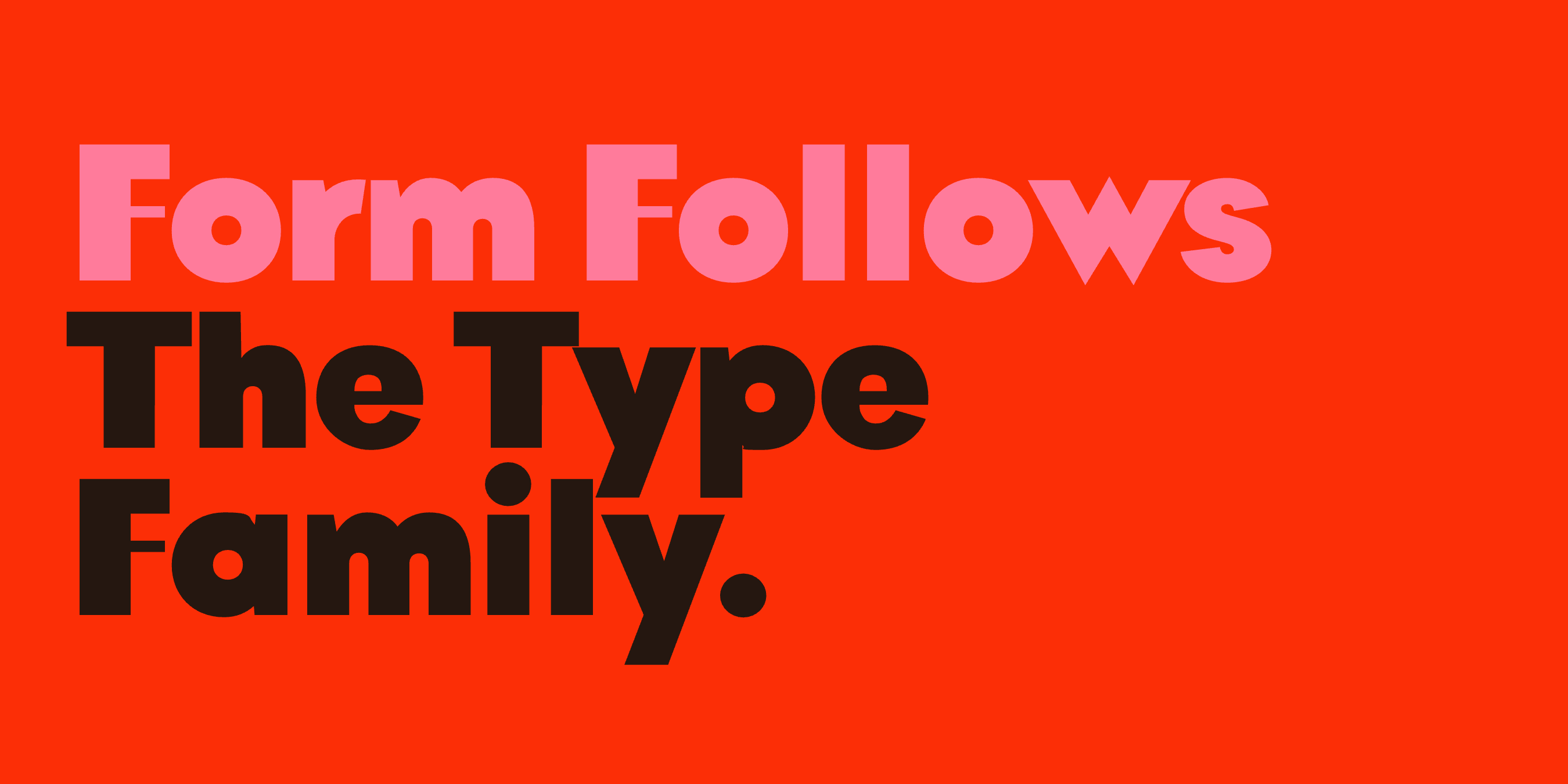
Bauhaus-Schriften: was eine Schrift zur Bauhaus-Schrift macht, und 11 zum Ausprobieren
Eine Bauhaus-Schrift besteht aus einfachen Formen: Kreisen, Bögen und geraden Linien, mit einer einheitlichen Strichstärke und ohne Verzierung. Dieser Ratgeber zeigt, woher dieser Stil kommt, woran man ihn erkennt, und 11 Schriften in diesem Stil, jede mit neun Schnitten und einer variablen Schrift.
Was eine Schrift zur Bauhaus-Schrift macht
Das Bauhaus war eine Gestaltungsschule, 1919 von dem Architekten Walter Gropius gegründet. Als sie 1925 in ihr eigenes Gebäude in Dessau zog, lief das Wort BAUHAUS in hohen, schlichten Großbuchstaben senkrecht an der Fassade hinunter. Im selben Jahr zeichnete Herbert Bayer, der an der Schule unterrichtete, sein Universalalphabet: nur Kleinbuchstaben, aufgebaut aus Kreisen, Bögen und geraden Linien. Eine eigene Schrift hat die Schule nie veröffentlicht. Bayers Alphabet blieb eine Zeichnung, bis Ed Benguiat und Victor Caruso daraus 1975 die ITC Bauhaus machten, die Schrift, an die die meisten beim Namen denken.
Die Futura, 1927 von Paul Renner gezeichnet, beruht auf denselben Ideen, obwohl Renner nie an der Schule unterrichtet hat. Erkennen lässt sich der Stil an diesen Merkmalen:
- Ein rundes o, nahezu ein perfekter Kreis.
- Ein einstöckiges a, oft auch ein einstöckiges g.
- Striche in einer Stärke, mit wenig oder keinem Kontrast.
- Buchstaben aus denselben wenigen Bauteilen, die sich deshalb ähneln.
11 Bauhaus-Schriften
Bauhaus Geo
Die Schrift in dieser Liste, die Bayers Alphabet am nächsten kommt. Das o ist ein Kreis, das a einstöckig, und der Strich hat eine einheitliche Stärke. Alternative Buchstaben machen sie geometrischer oder im Text besser lesbar. Für Architektur, Tech und minimalistische Marken.
Scal kommt in dieser Liste der Futura am nächsten: ein rundes a und o, spitze Enden an A, M, N, V und W und scharfe Schnitte an C, G und S. Die leichten Schnitte eignen sich für längere Texte, die kräftigen sind kompakt. Für Mode- und Beauty-Labels, Magazine und Restaurants.
Vole besteht aus Kreisen und geraden Linien wie die Bauhaus-Alphabete, mit kräftigeren, weicheren Formen. Die Punzen sind rund, a und g sind einstöckig, und die Strichenden sind gerade. Fünf Stilsets bieten andere Formen für a, g, M, N und mehr. Für Logos, Plakate und Verpackungen.
Eine runde Sans mit einfachen, modularen Formen: M und N sind oben gerundet wie das o. Sie wirkt freundlich und bleibt auch in kleinen Größen gut lesbar. Oft für Lifestyle-Marken und Konsumgüter verwendet und eine gute Sans für die Kombination mit Bauhaus Soft.
Die einzige Serifenschrift in dieser Liste. Eine kräftige, organische Serifenschrift mit weichen Ecken und etwas Kontrast zwischen dicken und dünnen Strichen. Sie ist unsere meistverkaufte Schrift. Für Beauty, Lifestyle, Verpackungen und Editorial, und sie passt zu jeder der Sans-Schriften hier.
Eine runde Schrift mit starkem Kontrast zwischen dicken und dünnen Strichen. Für Beauty-Marken, Verpackungen und Modemagazine.
Eine schmale Sans für Startup- und Tech-Branding, weniger geometrisch als Geo. Für Produktüberschriften, App-Screens und Pitch-Decks.
Eine klare Sans mit alternativen Buchstaben, zwischen Geo und Bau: weniger geometrisch als Geo, weniger rund als Bau.
Eine kräftige, breite Sans für Überschriften, Produkt-Screens und Dashboards.
Die verspielteste Sans hier, mit kräftigen Formen und lustigen alternativen Buchstaben. Sie passt gut zu Bauhaus Soft, für Kindermarken und verspielte Produktlinien.
Eine kräftige Blockschrift aus massiven, runden, modularen Formen. Für Kindermarken, Spielzeugverpackungen, Spiele und Logos.
- Bauhaus Soft + Bauhaus Geo. Soft für Überschriften, Geo für Text.
- Scal + Bauhaus Soft. Die spitzen Buchstaben von Scal neben den runden Ecken von Soft, für Mode und Beauty.
- Bauhaus Chez + Bauhaus Slim. Chez für Produktnamen, Slim für die Details, auf Verpackungen.
- Vole + Bauhaus Geo. Vole für Logo und Plakate, Geo für den Text.
Bauhaus-Typografie heute
Die Idee des Bauhauses war, von dem auszugehen, was ein Buchstabe leisten muss, und alles andere wegzulassen. Hundert Jahre später sind diese Formen in Logos, Schildern und Apps immer noch verbreitet. Mehr in diesem Stil gibt es in der Kollektion Bauhaus-Schriften, in unserem Beitrag über Schriften wie Futura und in unserem Ratgeber zu geometrischen Sans-Serif-Schriften.